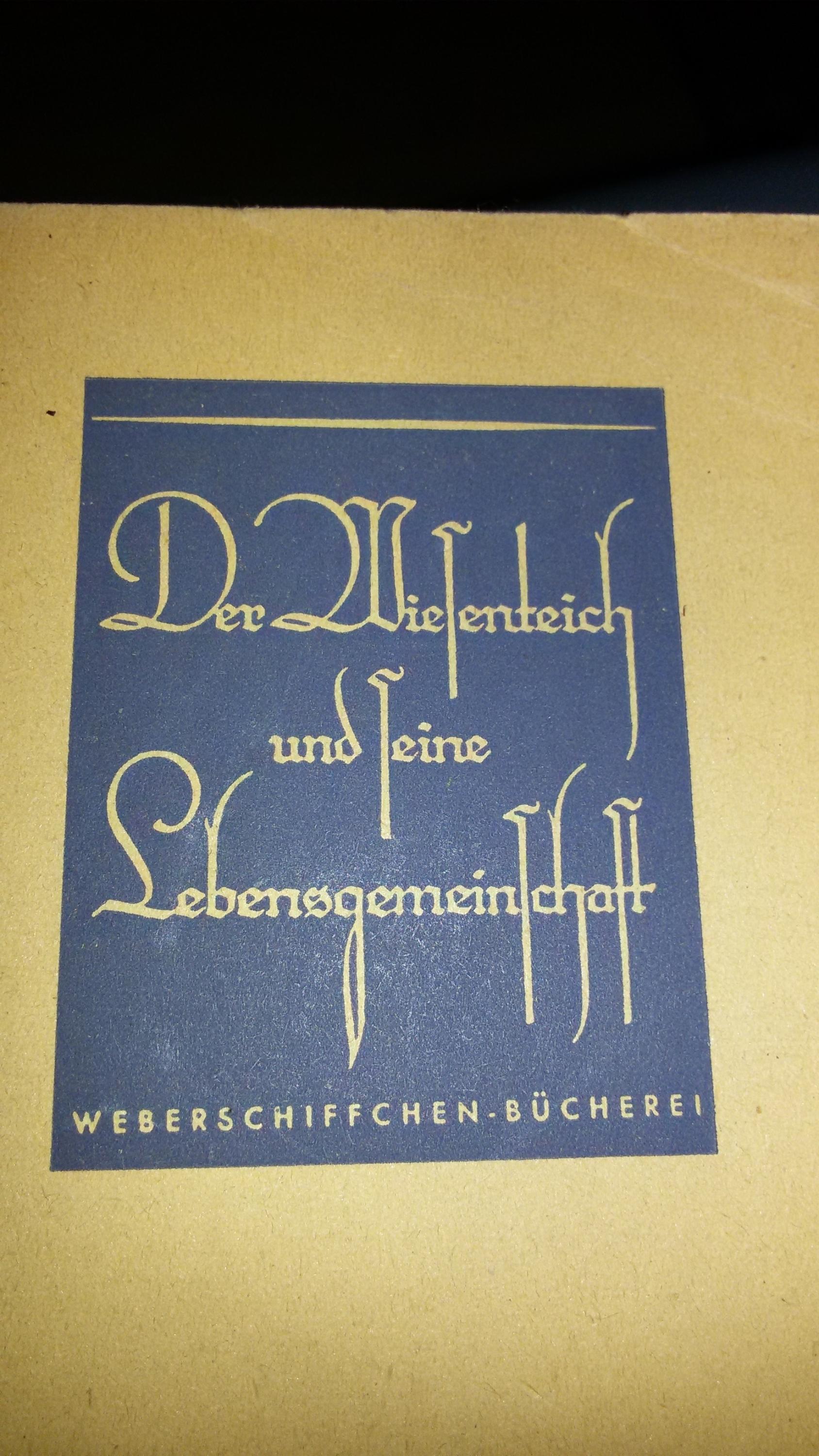
Suche diese Schrift vom Cover eines alten Buches (1936)
ich suche diese Schrift vom Cover eines alten Biologie-Buches von 1936.
Es heißt: "Der Wiesenteich und seine Lebensgemeinschaft". Es ist aus der Reihe "Weberschiffchen Bücherei", vom
Verlag J.J. Weber in Leipzig. Der Autor ist Julius Haarhaus. Bei der Suche,  geht es mir um die Schrift vom Cover des Buches! Die Schrift darf ruhig etwas kosten, freeware wäre auch schön.
Ja, nicht wahr? Diese Schrift ist wirklich
ein Eyecatcher!
Schade für mich, dass es Lettering ist.